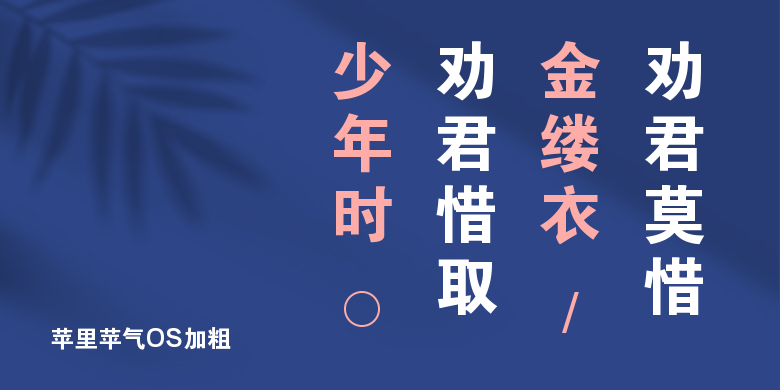
苹里苹气OS加粗
苹里苹气OS加粗,这款字体结构工整、笔画清晰,兼顾美观与易读性,适用于标题、正文、海报、包装、LOGO 等多种场景。字形优雅稳定,风格百搭耐看,适配日常排版与创意设计,让文字呈现更舒适、更具质感。苹里苹气OS加粗一笔一画,皆是细节,以均衡的比例、流畅的线条打造舒适视觉体验,字形端正大气,风格简约现代。无论是商业设计、品牌宣传还是日常排版,都能轻松驾驭,让文字更有格调与力量。苹里苹气OS加粗字体下载。